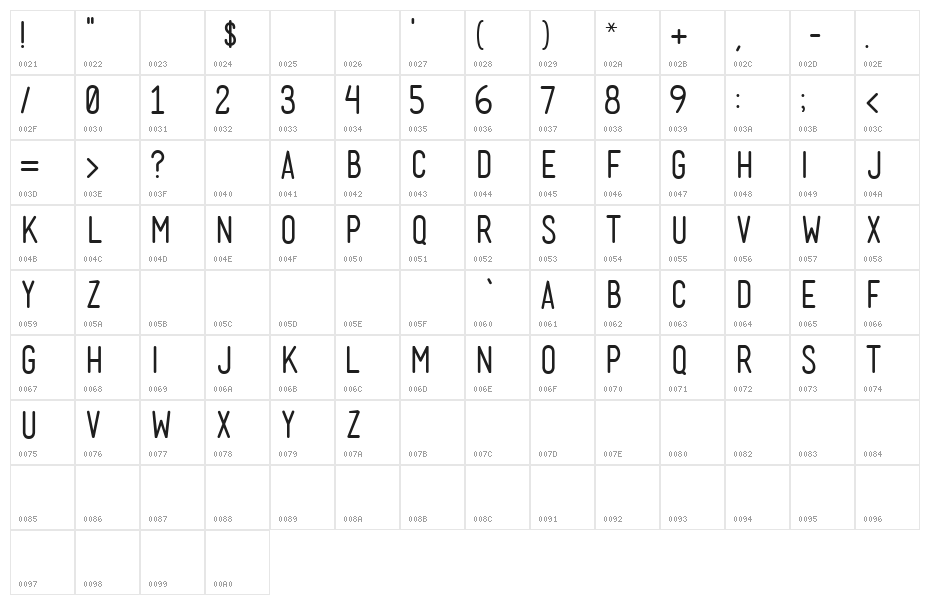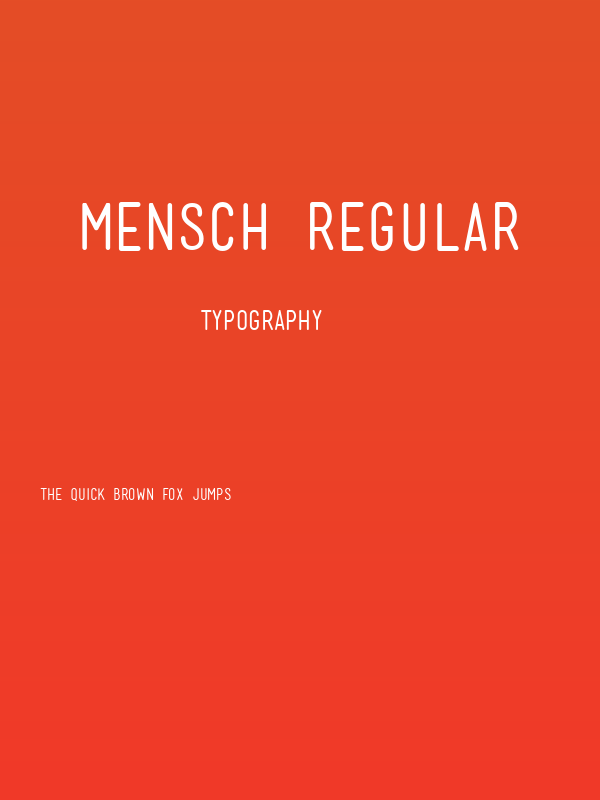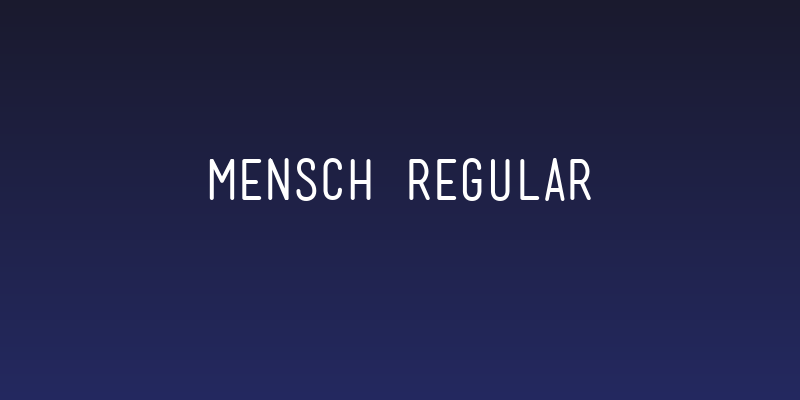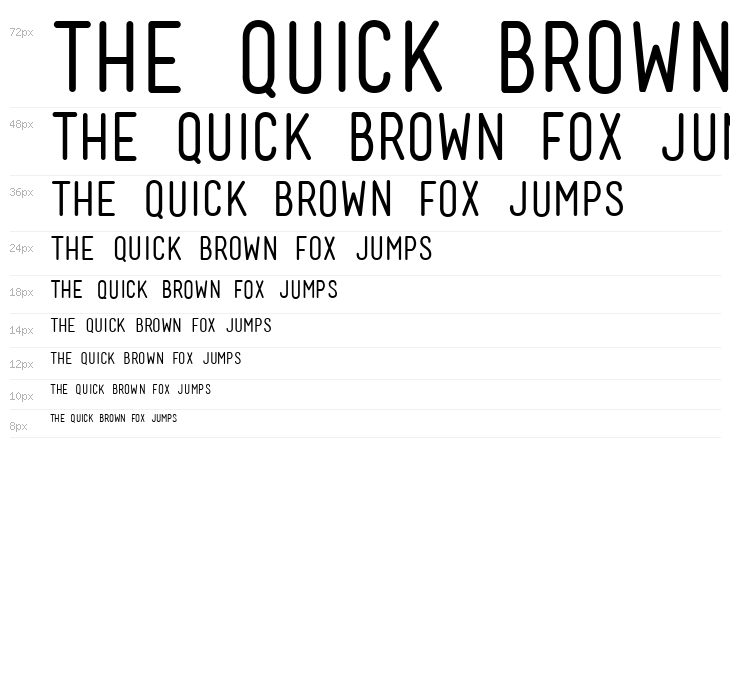
Mensch Regular Font
✎ Sans Serif
| Anwendungsfall | Headlines, Body text, Logos |
| Vorgeschlagene Projekte | Ideal for branding, web design, user interfaces, and print media where clarity and modernity are essential. |